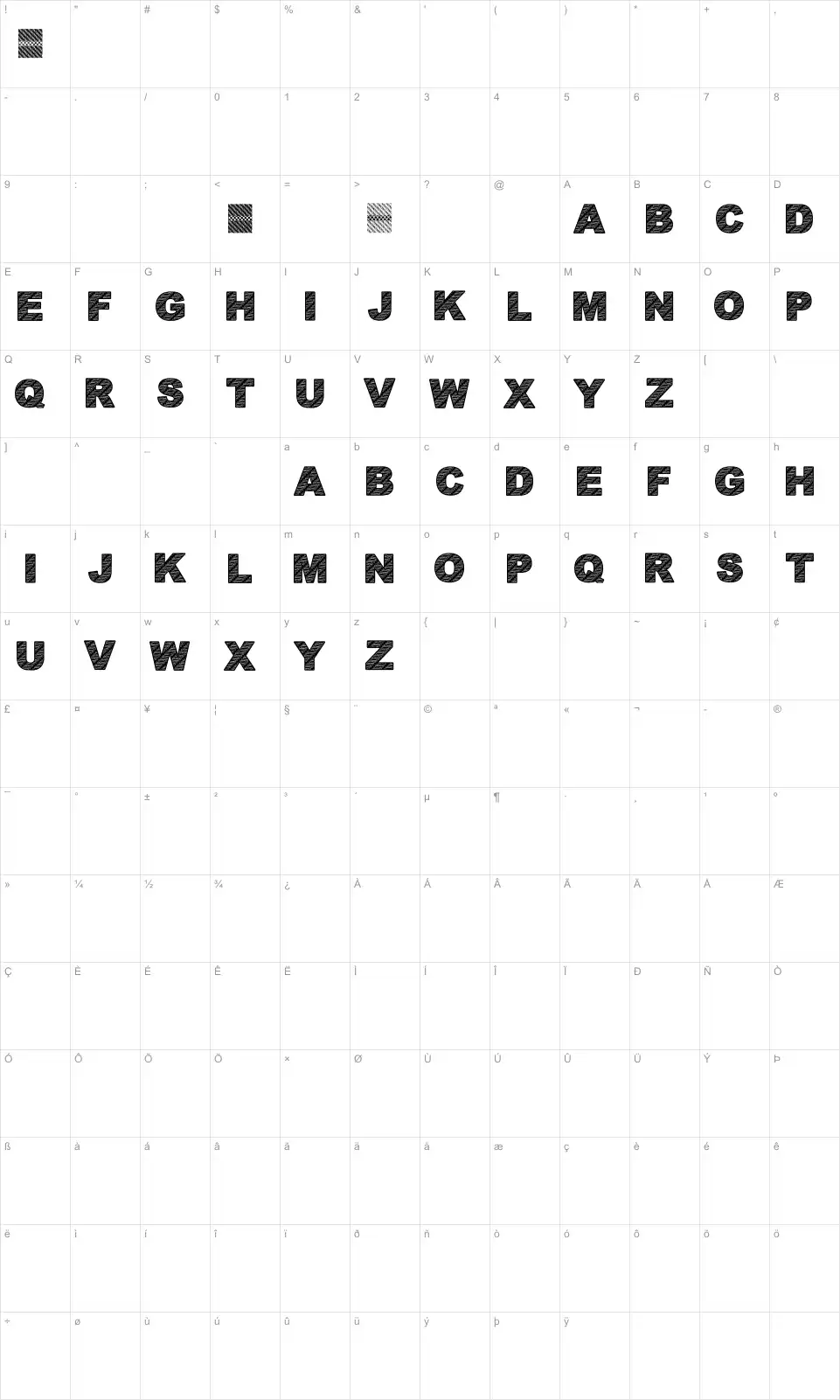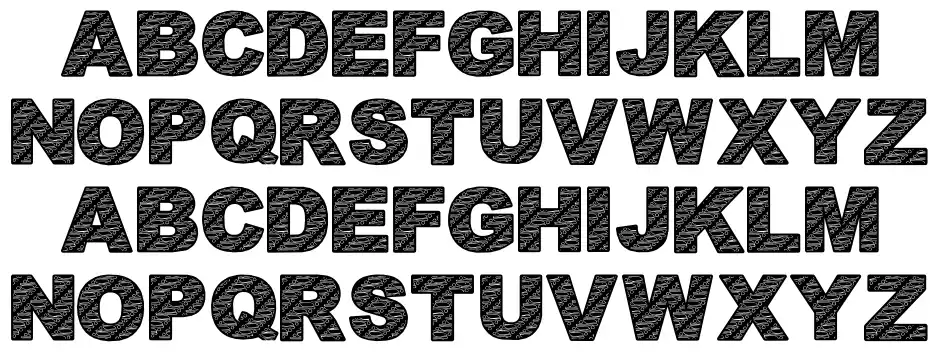
Batik Font 1
A Batik Font 1, criada pela Asia Culture, é uma fonte de categoria Fancy e Decorative. Com sua aparência única e rica em detalhes, essa fonte traz um toque sofisticado e vibrante a qualquer projeto. Se você está procurando por essa fonte, agora é a chance de descobrir mais sobre ela. Com esta categoria Fancy, é fácil criar designs impecáveis, seja para nomes de empresa, materiais de publicidade, ou até mesmo artigos de decoração. O formato TTF permite que você use essa fonte em qualquer aplicativo ou programa de design. Seja para personalizar uma mensagem ou até mesmo para criar um design exclusivo, a Batik Font 1 está aqui para ajudá-lo a alcançar seu objetivo. Se você gostar do que vê, você pode baixar a fonte ou gerar um preview personalizado online antes de começar a usá-la. Com 4005 downloads desde sua adição em 12 de julho de 2022, a Batik Font 1 é uma opção popular entre designers e criadores de conteúdo.
Designer: Asia Culture